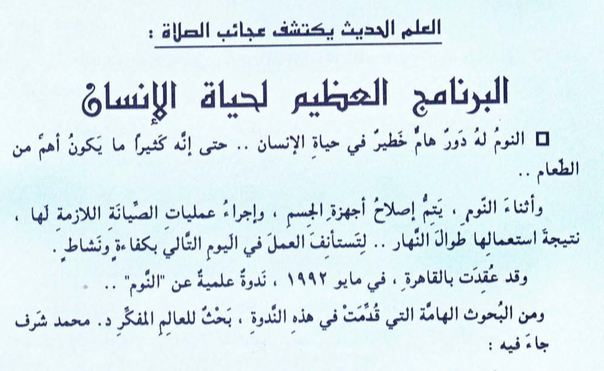
Weiß jemand, ob man im Arabischen den Mittelachsensatz verwenden kann? Mir ist klar, dass ich größere Textmengen aufgrund der Linksläufigkeit rechtsbündig setze. Ich habe aber den Fall, dass ich  in einer Sprechblase einen arabischen Text neben eine Illustration setzen muss. In meinem deutschen Original steht der Text innerhalb der Sprechblase zentriert – ob man das wohl auch auf Arabisch machen kann?
In einer Sprechblase kann man das durchaus tun, wie in allen anderen Sprachen auch. Auch ein kurzer deutscher Text funktioniert ja rechtsbündig oder zentriert gesetzt.
(Rechts: ) Iranische Atomwaffen
(Links:) Israelische Atomwaffen
(Auf dem Fahrzeug:) Sprengfahrzeug [Wassersprengfahrzeug]
(Sprechblase: ) Wir bleiben besser bei den (chemischen) Dingen
Danke Bertel für Deine Beispiele (auf die Idee nach arabischen Comics zu gucken hätte ich natürlich auch selbst kommen können ;-)) Ich wusste dass es z.B. im Chinesischen total unüblich ist – wenn auch nicht direkt „verboten“.